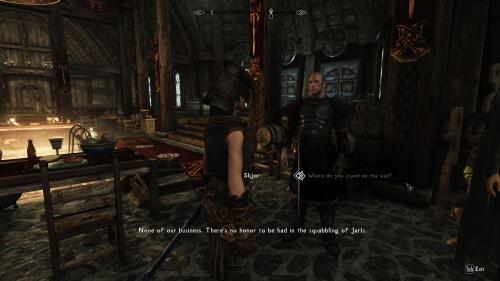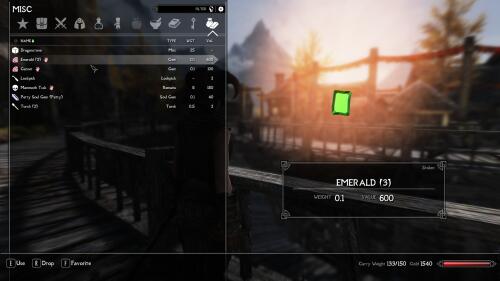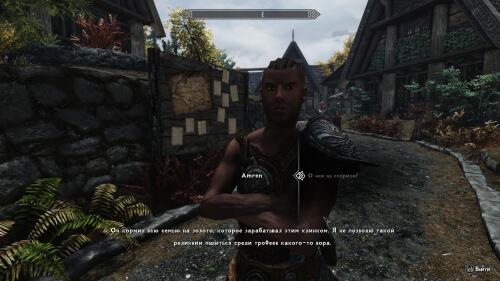
Sovngarde - тематический игровой шрифт. Разработан для усиления погружения в сеттинг игры Skyrim. Создан с поддержкой 8 языков, но в данном архиве предпочтение отдаётся русскому.
Имеет 2 стиля:
+ Light - менее жирный вариант написания, близок к стоковому шрифту по весу. Находится в папке "Light".
+ Bold - более жирный вариант написания, если вам кажется, что буквы "теряются" на экране. Находится в папке "Bold".
Это фиксится только изменением размера шрифта, в скайриме есть ограничение на размер шрифта и интерфейс не подстраивается под другой, не стандартный размер.